Существуют сотни, если не тысячи, веб-сайтов, предлагающих бесплатные шрифты, но большинство из них используют лицензирование Creative Commons, которое не всегда включает коммерческое использование. Если вы занимаетесь малым бизнесом или занимаетесь независимым творчеством и ищете ресурсы, это не сильно поможет. Что поможет, этот список веб-сайтов, которые предлагают бесплатные шрифты для коммерческого использования.
Я искал в Интернете в поисках веб-сайтов, которые предлагают бесплатные шрифты с предоставленными им определенными правами на коммерческое использование. Вы можете использовать любое из следующих проектов или продвигать свой собственный бизнес, не беспокоясь о юридических проблемах.
Google Fonts
Google Fonts позволяет коммерчески использовать их огромную библиотеку шрифтов, поэтому это логичное первое место для поиска любого веб-сайта или онлайн-проекта. Все шрифты используют Open Fonts License, которая предоставляет неограниченные права на использование, изменение, совместное использование или что-либо еще. Сама библиотека шрифтов огромна и, на мой взгляд, имеет 847 бесплатных шрифтов для использования в веб-проектах.
Шрифты Google обслуживаются самими Google, поэтому все, что вам нужно, — это ссылаться на них. Это означает, что вы можете изменить шрифт на лету и всегда будете использовать последнюю версию.
Шрифт Белка
Несмотря на сомнительное название, Font Squirrel — еще одно место, где можно найти бесплатные шрифты для коммерческого использования. Сайт огромен и имеет тысячи доступных шрифтов. Многие из них доступны для коммерческого использования. На сайте есть несколько действительно привлекательных шрифтов, я сам поставил пару для будущего проекта eBook, поэтому я уверен, что вы найдете здесь что-нибудь по душе.
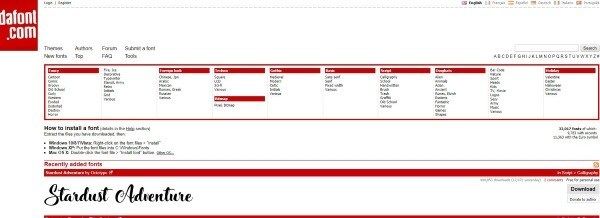
DaFont
DaFont — еще одно фантастическое хранилище бесплатных шрифтов. Здесь требуется больше внимания, поскольку в представленных материалах используются разные лицензии. Многие из них бесплатны для личного использования, а некоторые доступны для коммерческого использования. Выберите шрифт и посмотрите над кнопкой загрузки справа, чтобы точно узнать, какая лицензия предоставлена.
Я знаю, что авторы реагируют здесь, поэтому, если вы найдете что-то, что вам действительно нравится, у которого нет конкретной коммерческой лицензии, свяжитесь с автором шрифта и спросите. Всегда стоит попробовать правильный шрифт.
Библиотека шрифтов
Библиотека шрифтов является еще одним отличным хранилищем бесплатных шрифтов. Здесь их тысячи, охватывающих каждый тип и стиль. На сайте используются разные лицензии, в том числе GNU General Public License и Open Fonts License, поэтому стоит проверить их перед загрузкой. Тип лицензии отображается под кнопкой загрузки на странице каждого шрифта.
Преимущество библиотеки шрифтов заключается также в том, что на сайте размещены шрифты нелатинских символов. Это очень полезно для тех, кто занимается международными проектами. Мой друг-дизайнер использует это как источник арабских символов для проектов.
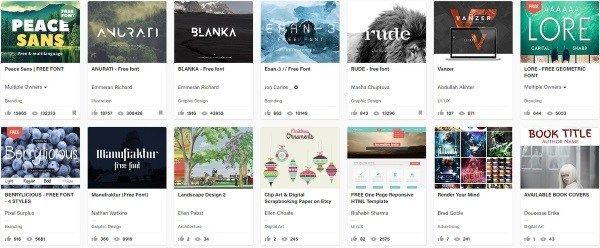
Downgraf
Downgraf — это сайт для дизайнеров, на котором есть пара страниц, содержащих ряд шрифтов для коммерческого использования. Это одна страница заметки. Он имеет некоторые очень красивые и очень современные шрифты, которые будут хорошо смотреться на многих сайтах. На странице есть «только» 21 шрифт, но они настолько высокого качества, что я был бы упущен за то, что не представил их здесь.
Behance
Behance — это еще один дизайн-сайт, в котором есть целый ряд шрифтов. Эта страница содержит сотни шрифтов для коммерческого использования, предоставляемых в рамках лицензии. Некоторые из них очень хорошие, а некоторые не очень. Как и на других сайтах, на которые есть ссылки в этом посте, для поиска правильного шрифта потребуется некоторая фильтрация. Это немного усложняет Behance из-за того, что вам приходится заходить в каждый из них, чтобы увидеть сам шрифт. Тем не менее, этот ресурс стоит добавить в закладки, если вам часто нужны новые шрифты.
MacAppWare
MacAppWare имеет приложение, которое предлагает 679 бесплатных шрифтов для коммерческого использования. Если вы используете Mac и не хотите использовать приложение для поиска шрифтов, возможно, стоит попробовать. Вам необходимо заполнить форму с указанием своего имени и адреса электронной почты, чтобы получить доступ, но с большим количеством доступных адресов электронной почты, которые не должны быть препятствием для доступа к шрифтам.
Создай свой путь
В Design Your Way есть страница, посвященная коммерческому использованию шрифтов, которая содержит 41 пример отличного дизайна. Это еще один ресурс, который отдает предпочтение качеству, а не количеству, и здесь есть несколько отличных шрифтов. Есть хорошее сочетание стилей, включая почерк и некоторые скандинавские дизайны, которые я никогда раньше не видел. Это определенно сайт, который стоит посетить для вашего следующего проекта.